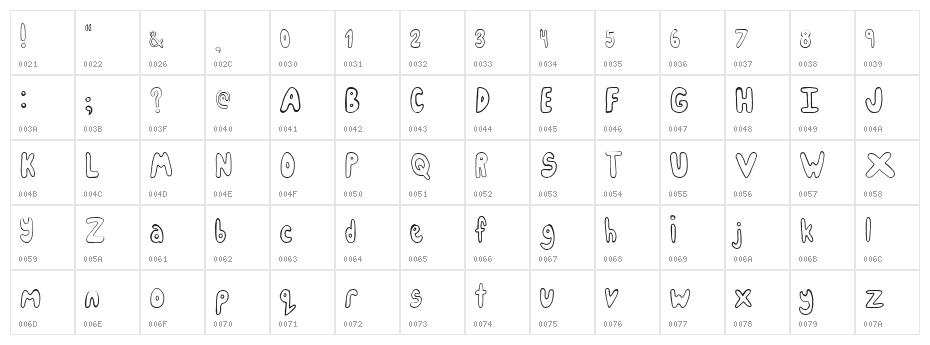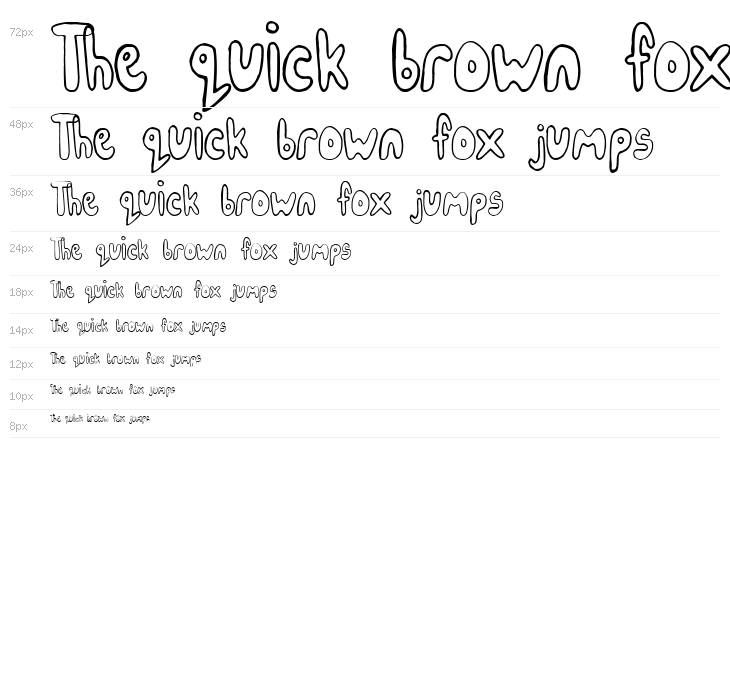
IceCreamParty Font
| 全体的なスタイル | Playful, Whimsical |
| 用途 | Headlines, Logos, Invitations |
| おすすめプロジェクト | Ideal for children's books, party invitations, playful branding, and creative posters. |